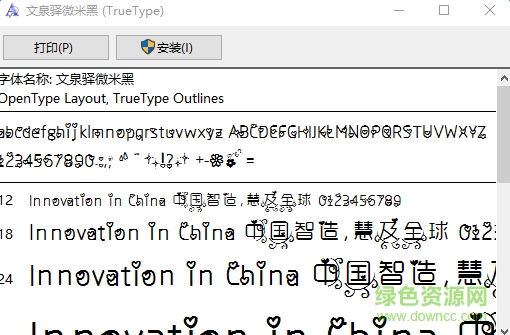
繞樹三匝字體是一款很有特色的電腦個(gè)性字體,這款字體寫出來的字是很好看的,不僅字形好看,而且很實(shí)用,可以用在很多方面,歡迎大家來綠色資源網(wǎng)下載。
繞樹三匝字體這款字體是真的很不錯(cuò),是一款充滿戀愛味道的甜蜜字體,用于藝術(shù)設(shè)計(jì)是再合適不過了,喜歡的朋友可以來綠色資源網(wǎng)下載。